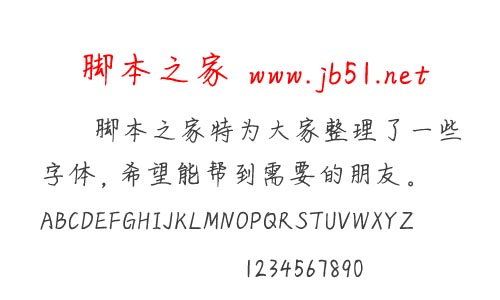
天邊牧白云字體是思雨字庫推出的一款手寫風(fēng)格藝術(shù)字體,字體筆觸粗細(xì)適中,書寫流暢灑脫,具有很好的視覺感,適合應(yīng)用于藝術(shù)設(shè)計、平面宣傳設(shè)計、網(wǎng)頁設(shè)計,書法字帖等領(lǐng)域,歡迎喜歡天邊牧白云字體的朋友前來下載使用。